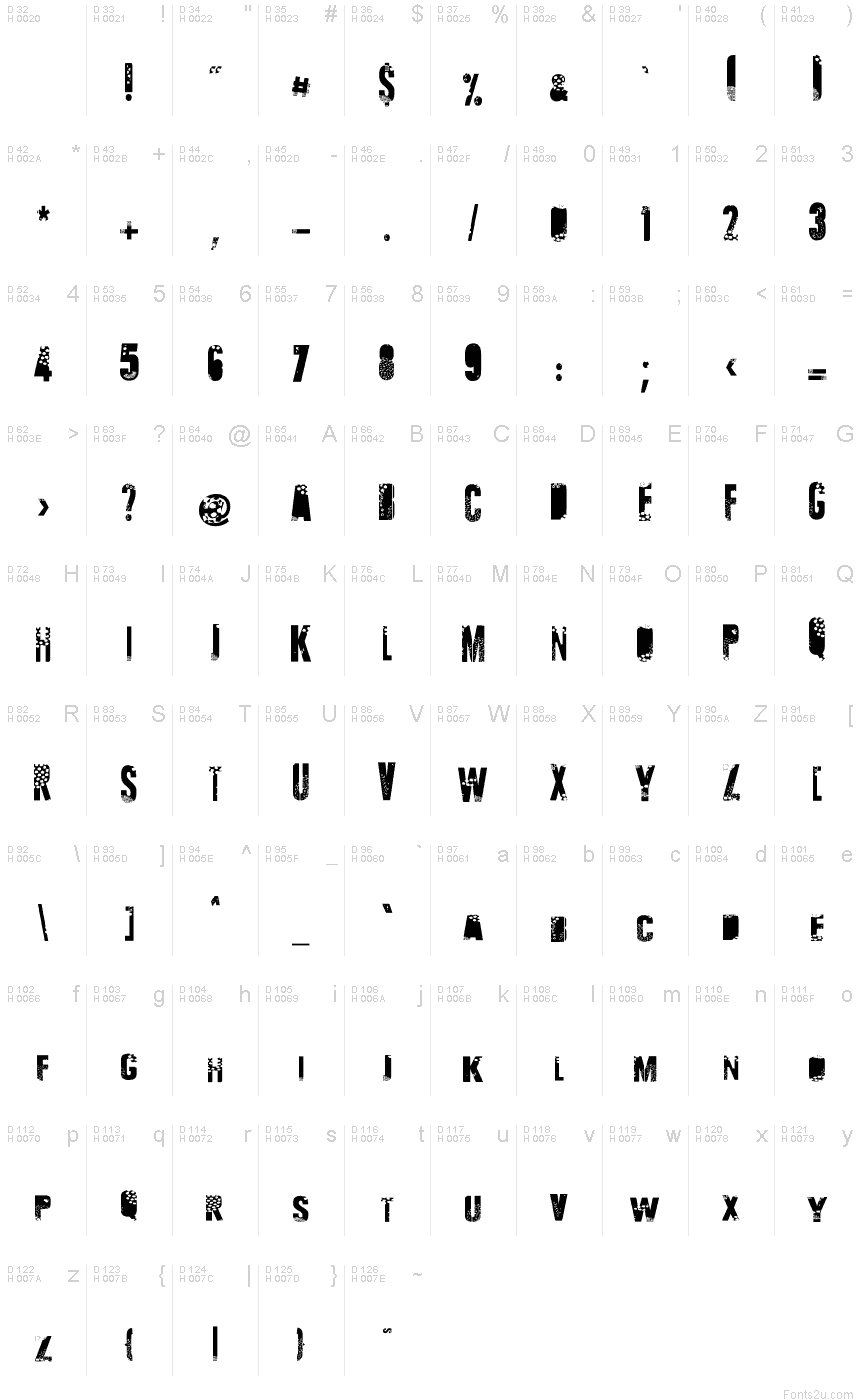
Talvez Assim autorstwa Pintassilgoprints to darmowy krój akcydensowy o erodowanym charakterze, zbudowany z wysokich, masywnych wielkich liter oraz chropowatych, popękanych powierzchni. Drobne, organiczne ślady przerywają kanciaste sylwetki, podczas gdy rozproszone zadrapania i zużyte krawędzie nadają całości rzemieślniczy charakter druku, choć stopień uszkodzenia wyraźnie różni się w zależności od litery.
Jego ksero-punkowy styl pasuje do plakatów koncertowych i okładek albumów. Marki streetwearowe, gadżety deskorolkowe oraz okładki alternatywnych magazynów mogą czerpać z tej samej poturbowanej tekstury, zwłaszcza w projektach powiązanych z muzyką podziemną i kulturą uliczną.
Ostatnio dodano dodatkowe glify i dostosowano pary kerningu.